Минкульт Украины создаст свои шрифты: Надо избавиться от русской системы
Министерство культуры Украины планирует создать банк украинских шрифтов и отказаться от использования русских. Об этом сообщает Минкульт страны.
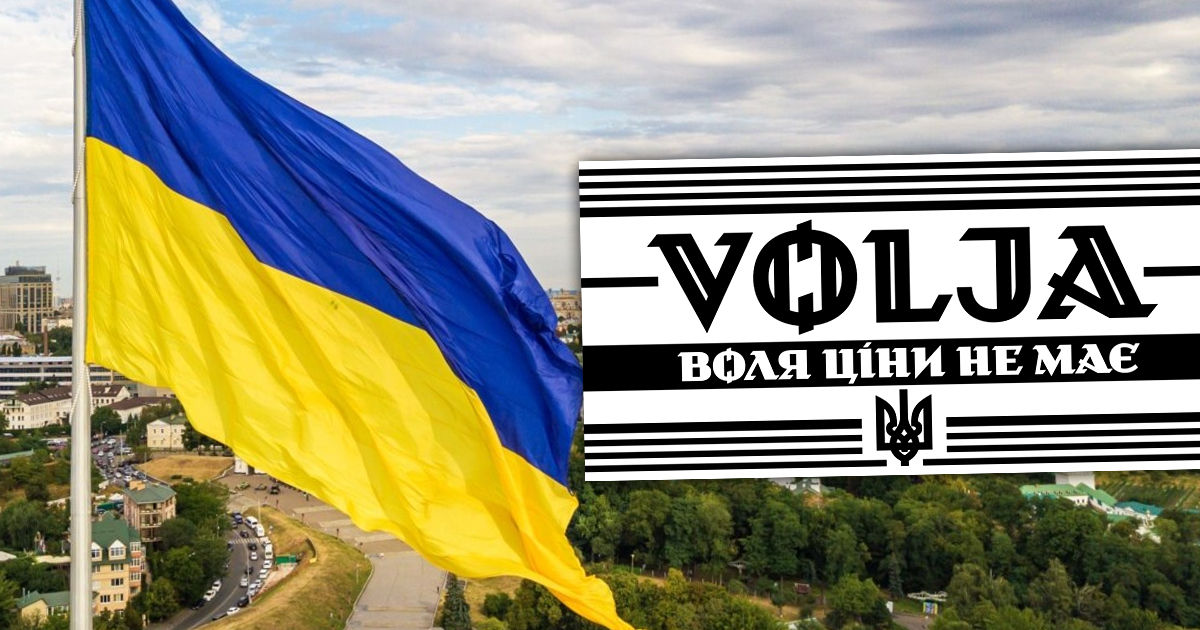
Как отметил и.о. Министра культуры и информационной политики Ростислав Карандеев, Украина должна прекратить использование шрифтов российского происхождения, заменив их украинскими, передает rbc.ua
"У нас есть символы своей суверенности и независимости, которые идентифицируют наше государство, его историю, культуру, язык и графическое выражение этого языка", - сказал он.
Верховная рада планирует отказаться от использования в своих внутренних документах русского шрифта "Ижица" и производных от него. Его планируют заменить дизайнерским шрифтом "Воля". Его разработала украинская шрифтовая дизайнер Марчела Можина на базе литераций главного художника УПА Нила Хасевича.
"Письменность как составляющая языка является одним из элементов национальной идентичности. В Украине давно действует запрет на использование русского языка в документации, поэтому стоит избавиться и от русской системы глифов, то есть шрифтов. МКИП запланировал проведение отбора и формирования банка уникальных украинских шрифтов", - отметил Карандеев .